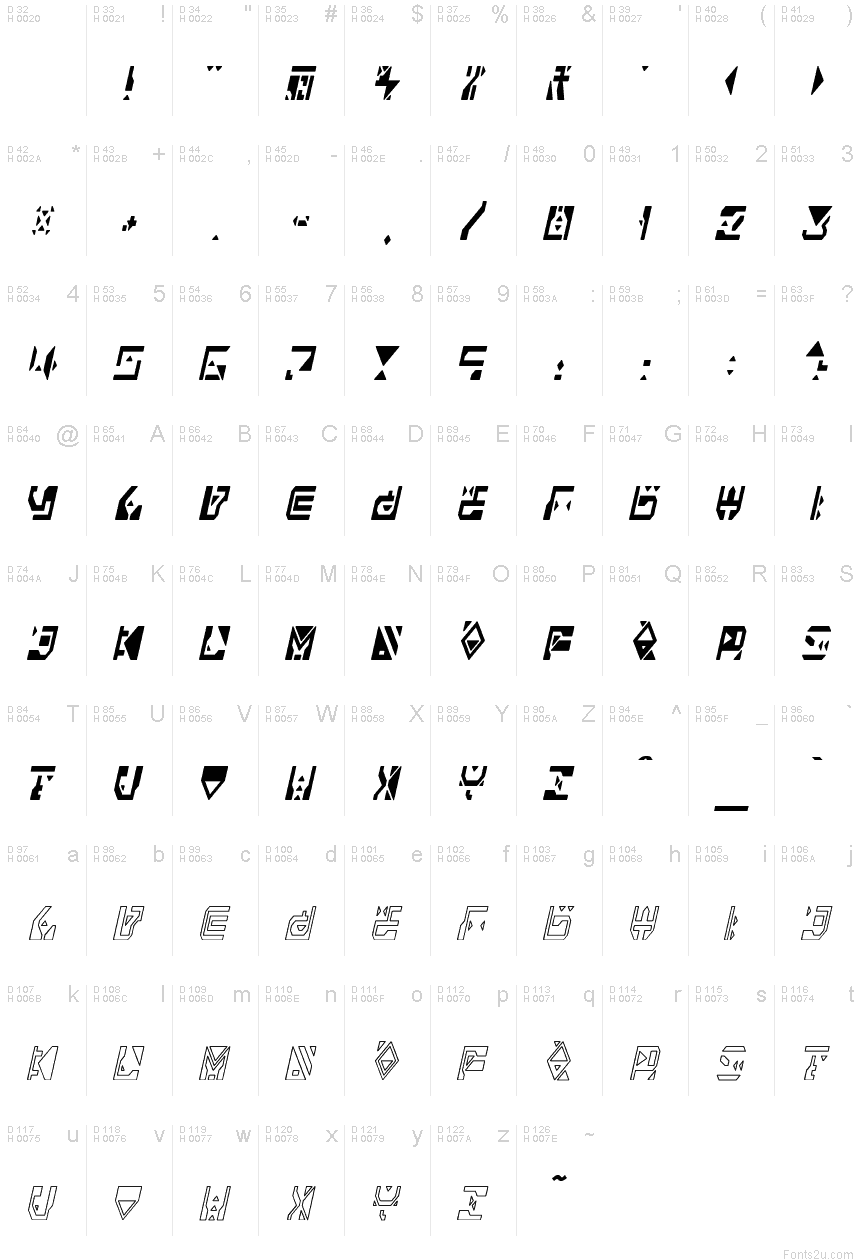
Alianna von Ray Larabie ist eine futuristische Display-Schrift, die wie aus kantigen Neon-Glassplittern geätzt wirkt. Die hohen, geneigten Formen und hohlen Konturen erinnern an außerirdische Schaltkreise oder die Fassade einer Sci-Fi-Megacity – scharf, geradlinig und voller Dynamik, selbst bei einzelnen Wörtern. Das kompakte Spacing verleiht Überschriften eine dichte, kodierte Energie, die sofort nach „ferner Zukunft“ und „High-Tech“ schreit.
Diese kostenlose Schrift glänzt auf Spieltiteln, Sci-Fi-Buchtiteln, Filmplakaten, Tech-Konferenzgrafiken, Festival-Flyern und EDM-Albumcovern. Sie eignet sich hervorragend für Logos und kurze Überschriften, bei denen die Buchstaben zugleich Typografie und Zeichensystem sein sollen. Kombinieren Sie Alianna in kleinerem Text mit einer einfachen, neutralen serifenlosen Schrift, damit die Lesbarkeit erhalten bleibt, während ihre elektrische Geometrie im Mittelpunkt steht.